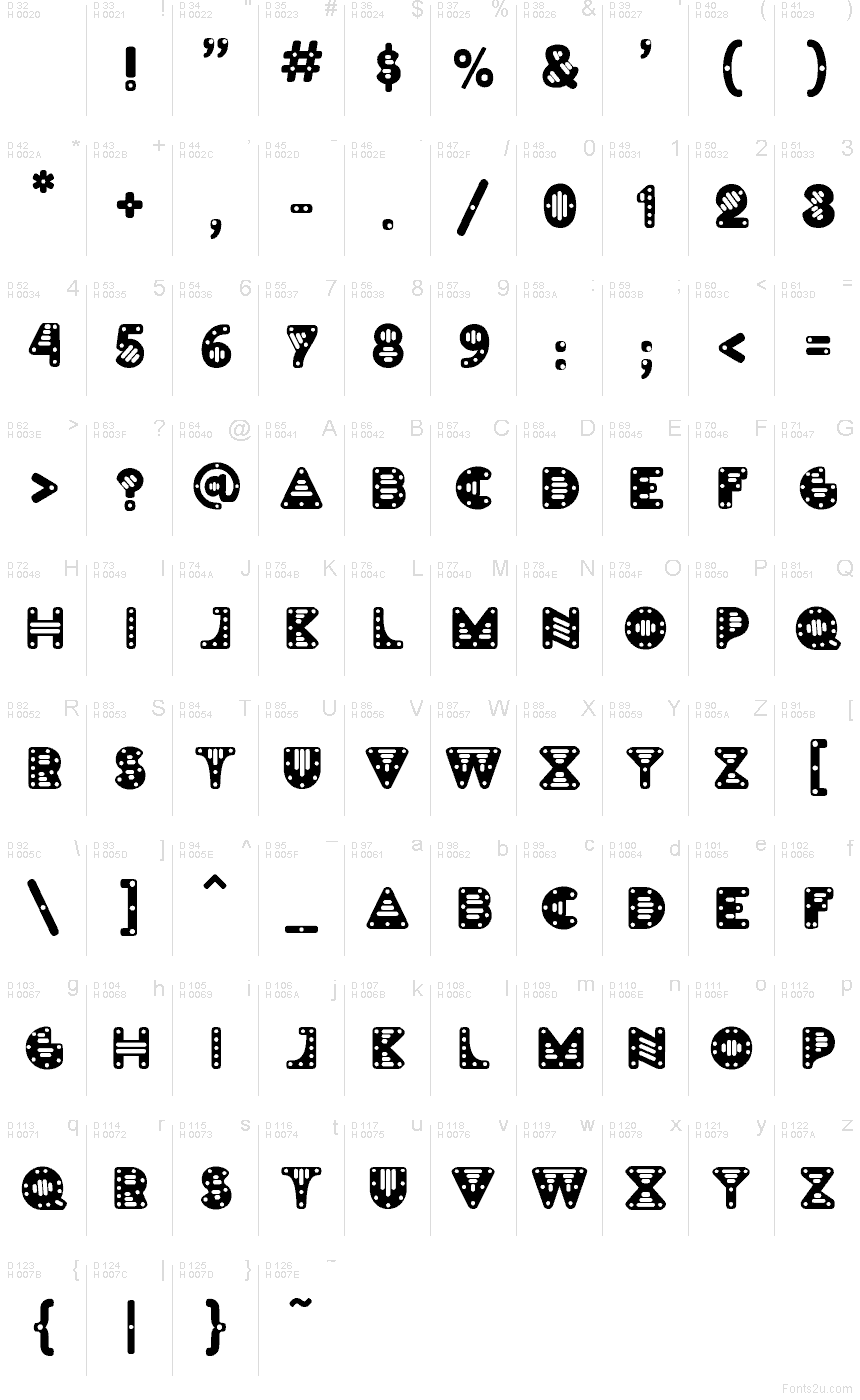
Steel Plate od Shanaf Studio je bezplatné dekorativní display písmo s masivními, zaoblenými verzálkami, které jsou protnuty štěrbinami, příčkami a kruhovými značkami připomínajícími nýty. Detaily se písmeno od písmene liší.
Tyto perforace evokují panely strojů, větrací otvory a kovové konstrukce, takže se nápis může stát přirozenou součástí industriálních ilustrací na hudebním merchandisingu, herní grafice nebo plakátech na akce, místo aby působil odděleně od grafiky. Na obálkách časopisů nabízejí rozmanité vnitřní tvary písmen hotový systém vzorů, který lze opakovat v rámečcích, úvodech rubrik či dalších redakčních dekorativních prvcích napříč celým článkem.